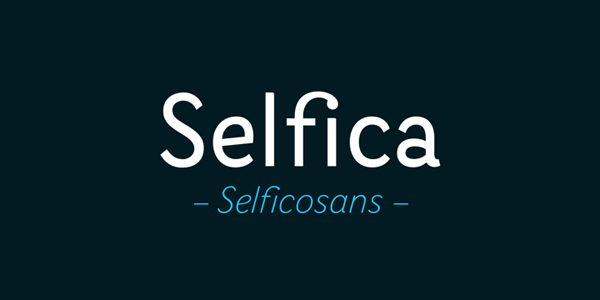
Comece uma bela manhã com uma nova família de fontes. Este é a Sans Serif Type Family que está sendo apresentado. Você certamente ficará satisfeito ao usá-la em seu projeto de design. Introduzimos agora Selfica Font Family. A Sans serif do tipo Selfica, criada e compartilhada pela Nootype. O estilo da tipografia tem um formato semi-condensado geometrico. Selfica inclui várias ligaturas estilizadas e uma ampla gama de pesos. Esta família de fontes pode ser usada como fonte para headlines chamativas, títulos menores ou como fonte do texto.